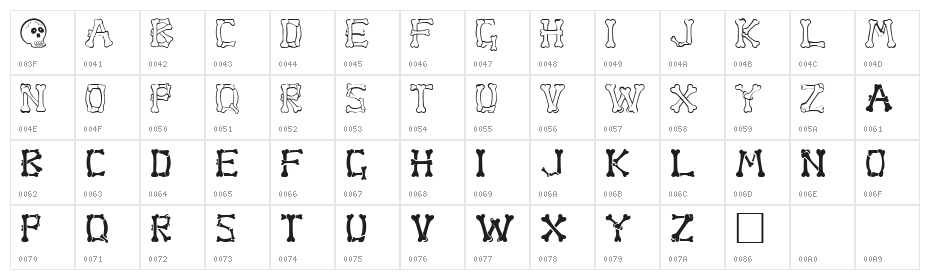
Bone Regular Font
| Proyectos propuestos | Ideal for Halloween-themed graphics, horror movie posters, children's spooky storybooks, and themed party invitations. |